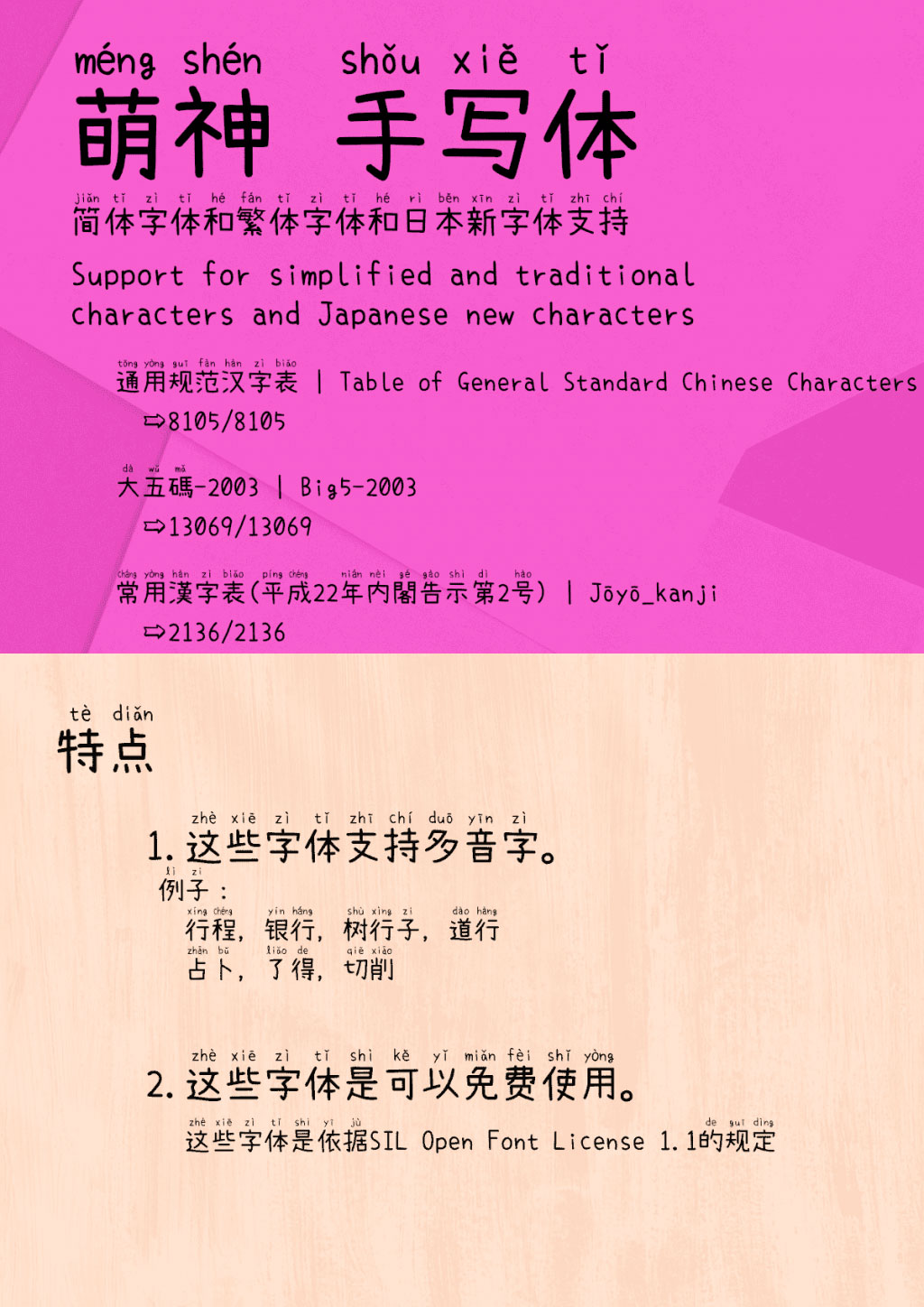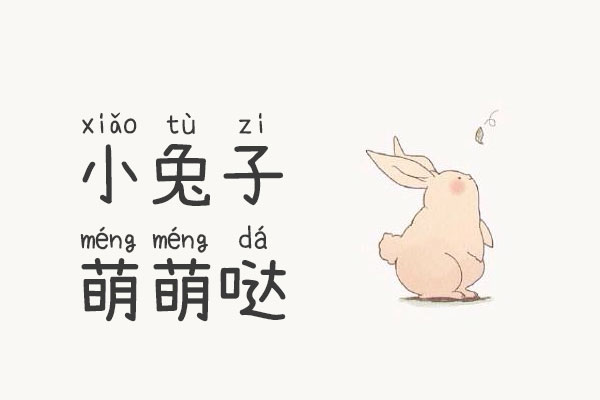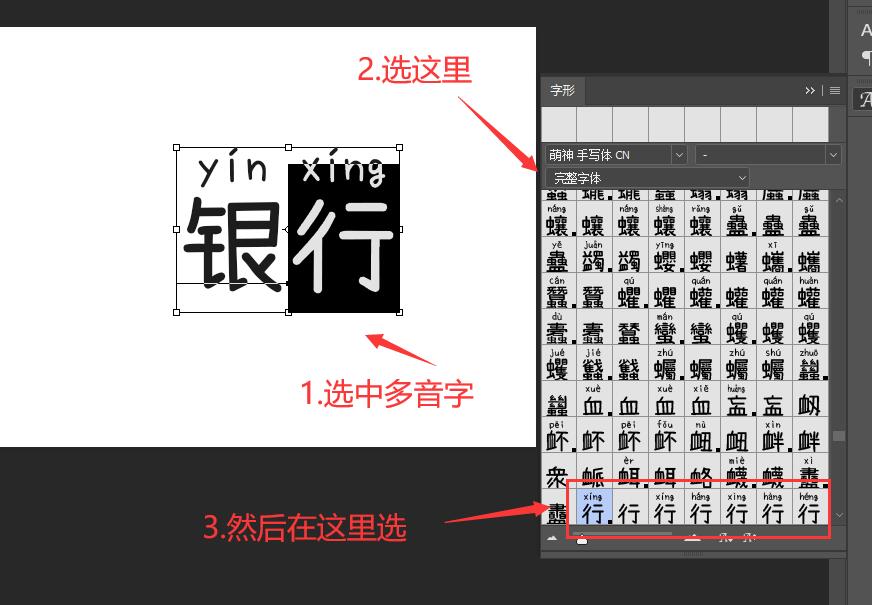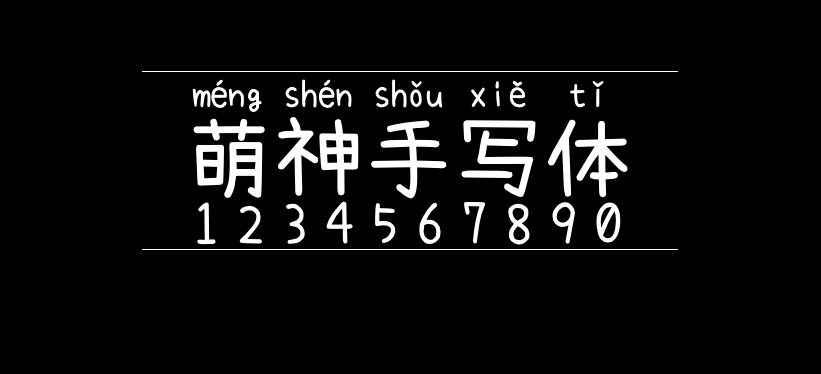
萌神手写体
萌神项目是日本的MaruTama创建的一个帮助学习中文的项目,萌神手写体(Mengshen-Handwritten / 萌神 手写体 CN)是基于已免费开源的“小赖字体”进行改造的一款免费商用中文字体,附带文字的拼音,这是一种用来帮助学生更快地学习和阅读汉语的字体。基本上是可以显示日语、简体字和繁体字的字体,是在简体字和繁体字中加入拼音的字体的制作。
萌神手写体实现了上下文替换(feature of“rclt”at GSUB)以支持多音字。另外,还可以使用Unicode IVS(表意文字变体选择器)来切换到不同的拼音。
萌神手写体的字符比较齐全,覆盖了GB2312标准的简体6763字,以及繁体国字标准的所有字符,基本不存在缺字现象。萌神手写体是依据SIL Open Font License 1.1授权协议免费公开,您可以免费用于个人及商业用途。